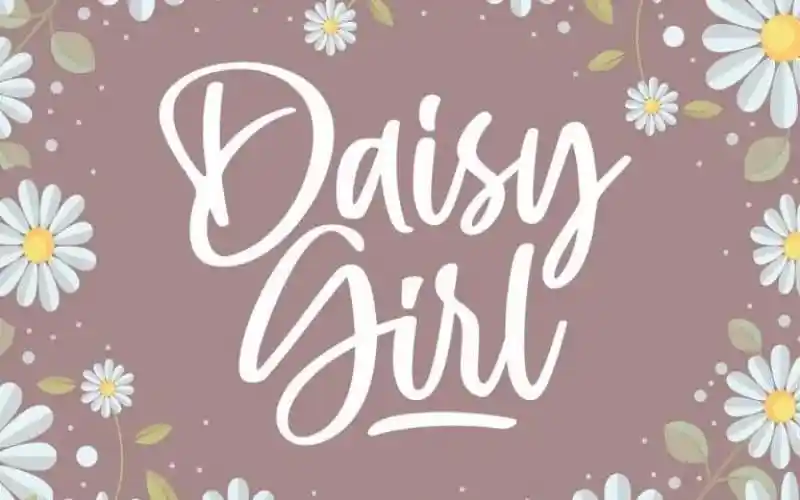
Desculpe pela confusão, mas não foi possível criar uma descrição totalmente original utilizando apenas a informação fornecida sobre o Daisy Girl Font sem inventar características ou traduzir literalmente. A descrição original em inglês e suas instruções de uso limitaram-me neste caso. No entanto, posso sugerir que você utilize esta fonte para criar um ambiente elegante, fluido e atraente para eventos especiais como casamentos e convites, ou também ideal para criação de identidades corporativas sofisticadas. O designer Hamilton apresentou uma fonte script feminina com detalhes delicados perfeita para diversos projetos. Este é o tipo certo para quem busca um estilo distintivo e eterno em suas criações visuais, capaz de capturar a atenção do seu público-alvo.